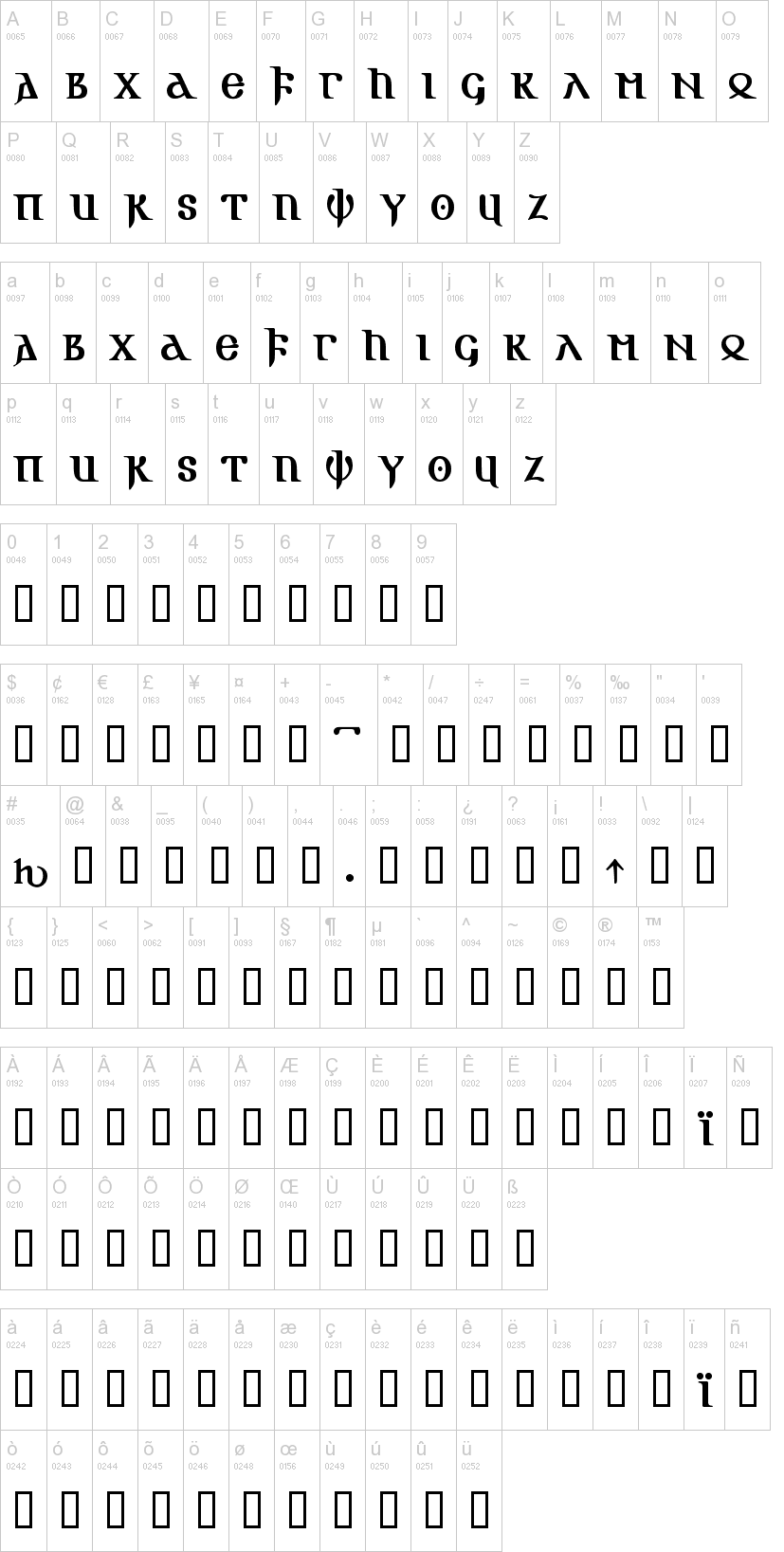
Gothic AOE字体是由美国设计师 Brian J. Bonislawsky 创作的一种古风的黑体字体,它带有一种装饰性和神秘感,经常被用于设计海报、标志、标题等等。字体的字形清晰、稳定,具有高度辨识度,同时也非常具有可读性,适合用于大字号的设计。它的设计灵感来自于中世纪高卢地区的手写字母,因此具有浓郁的欧洲中世纪风格。Gothic AOE字体一共包含了六种不同的字重(Regular、Medium、Bold、ExtraBold、Heavy、Black),可以根据需要选择不同的字重来达到不同的效果。内容介绍
Gotic AOE是一款非常不错的手写艺术字体,具有很好的视觉感,适合于文化类的宣传设计、商业类品牌的广告和产品包装设计以及个性化文字排版等较多场景。